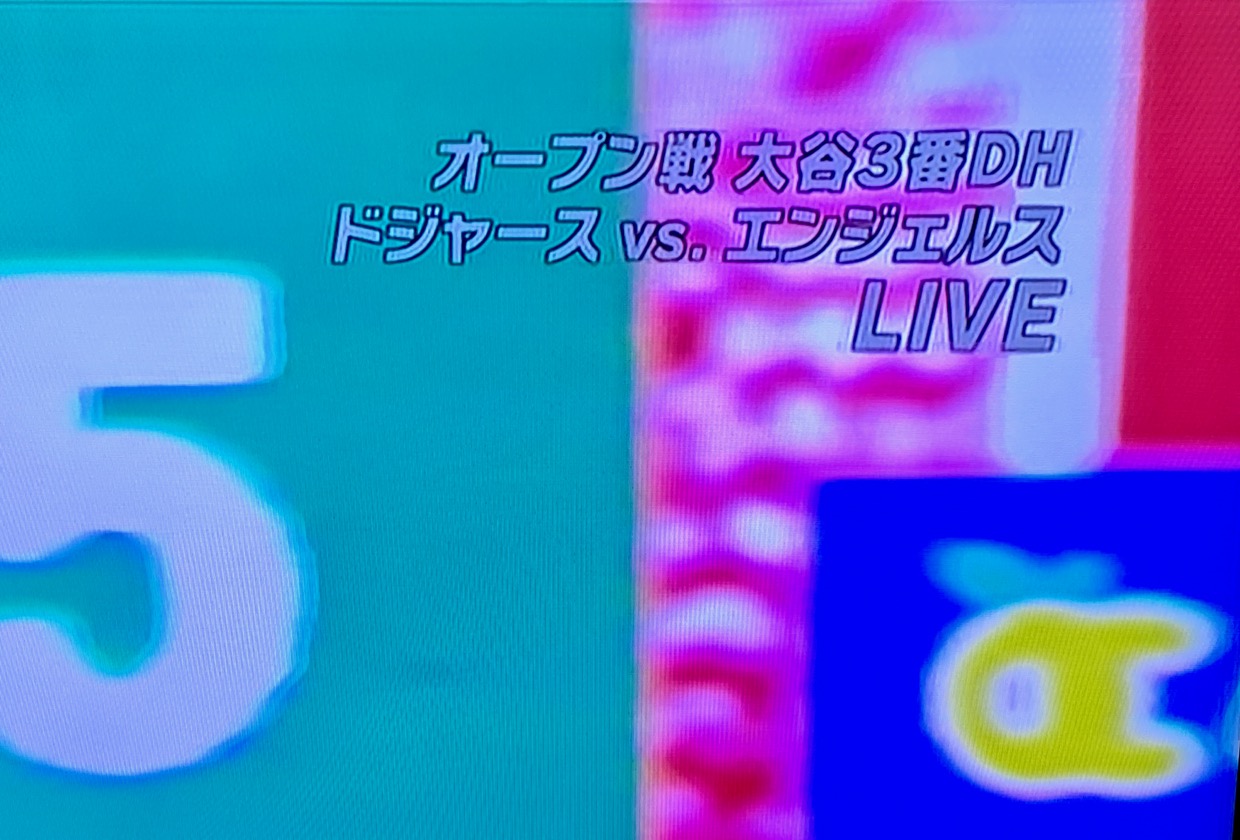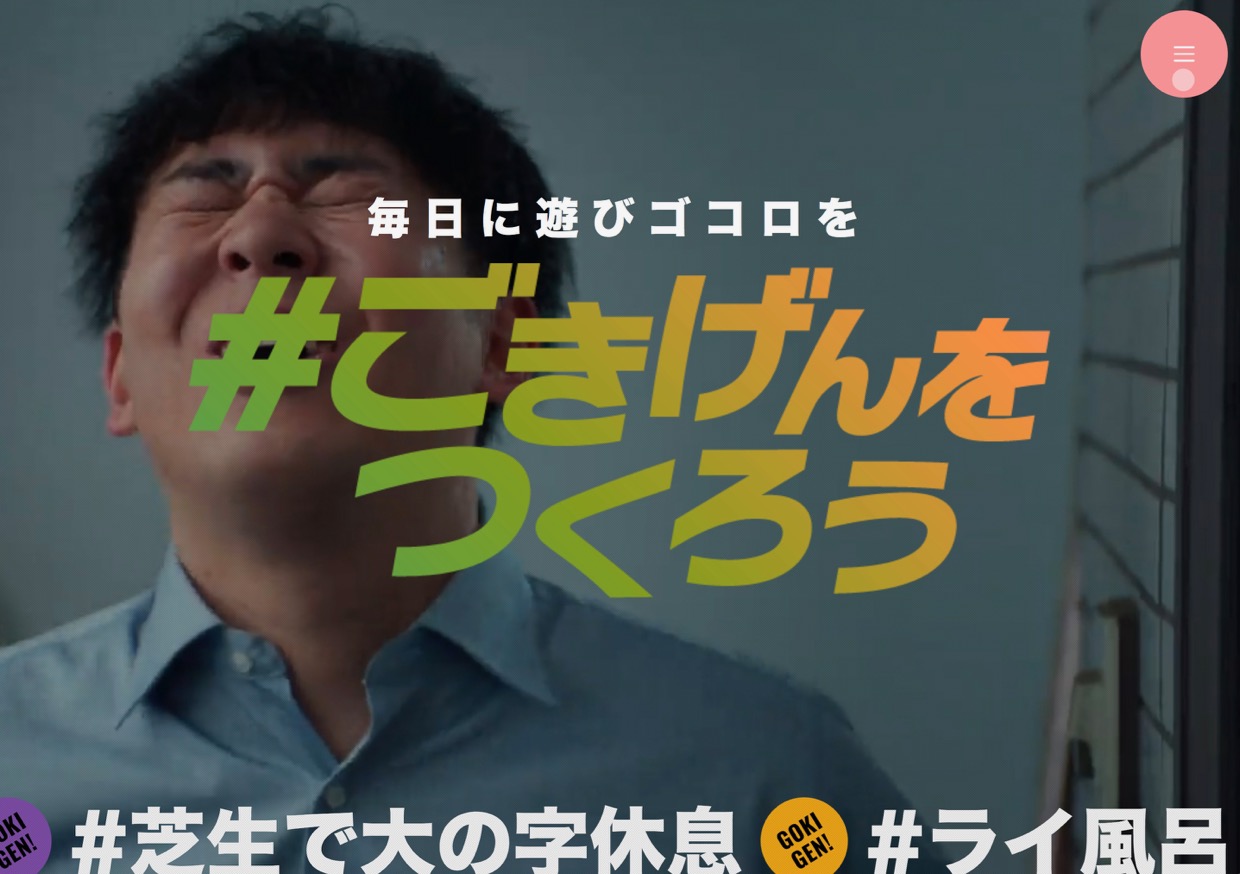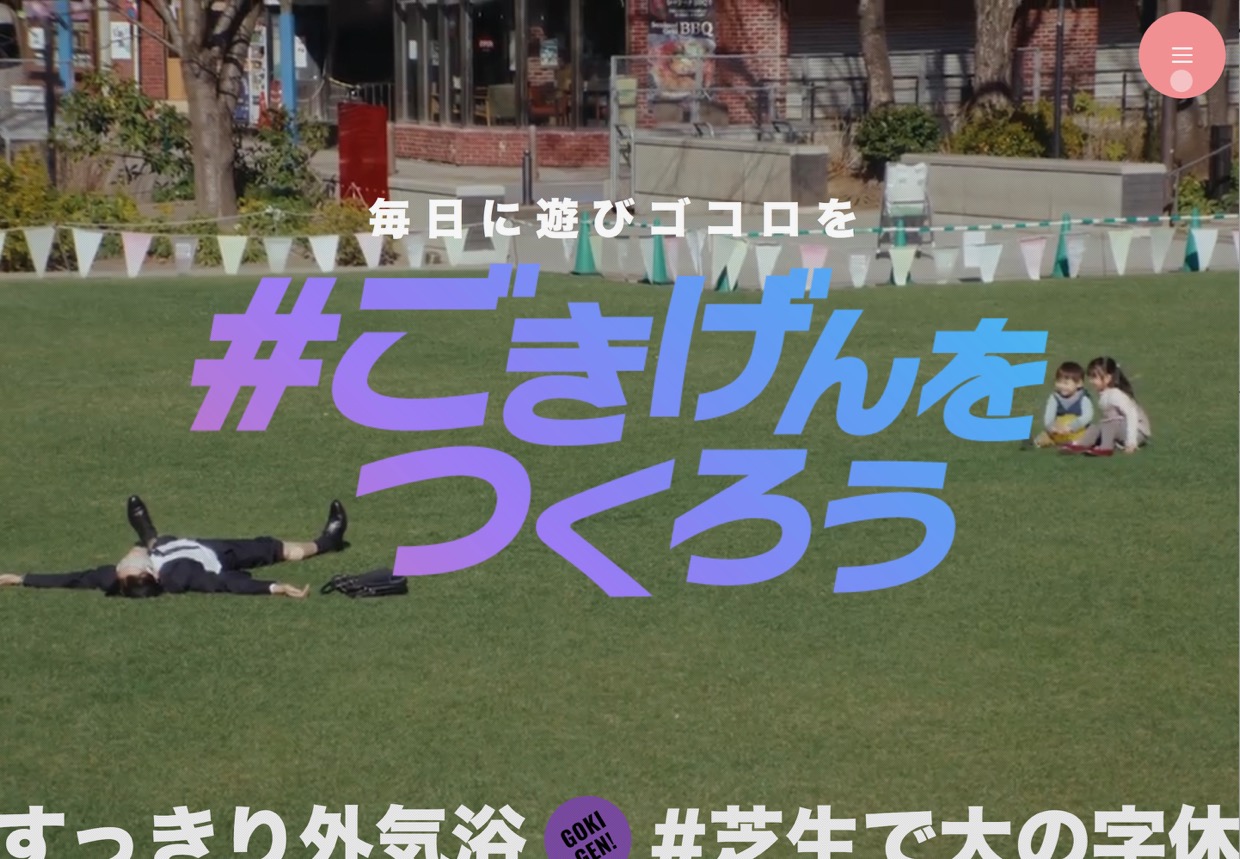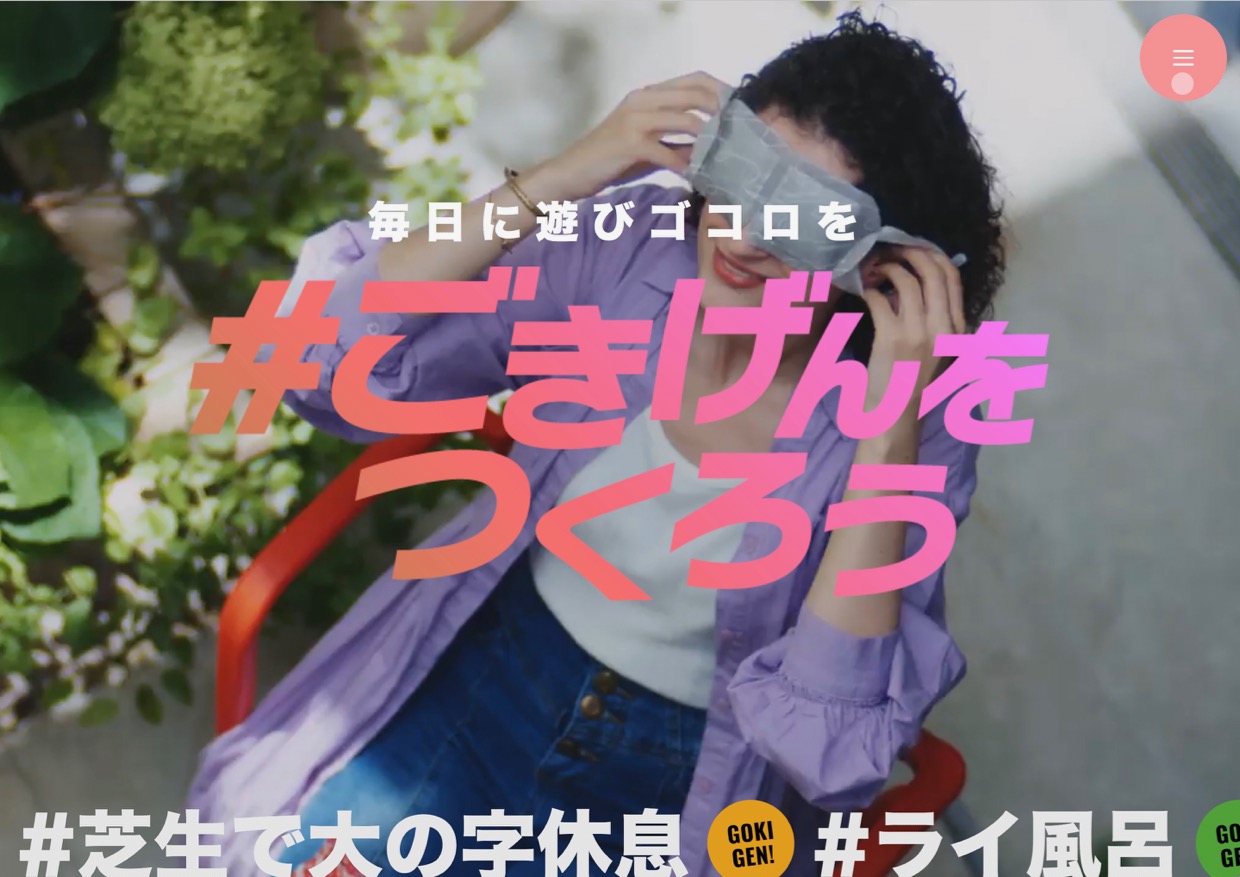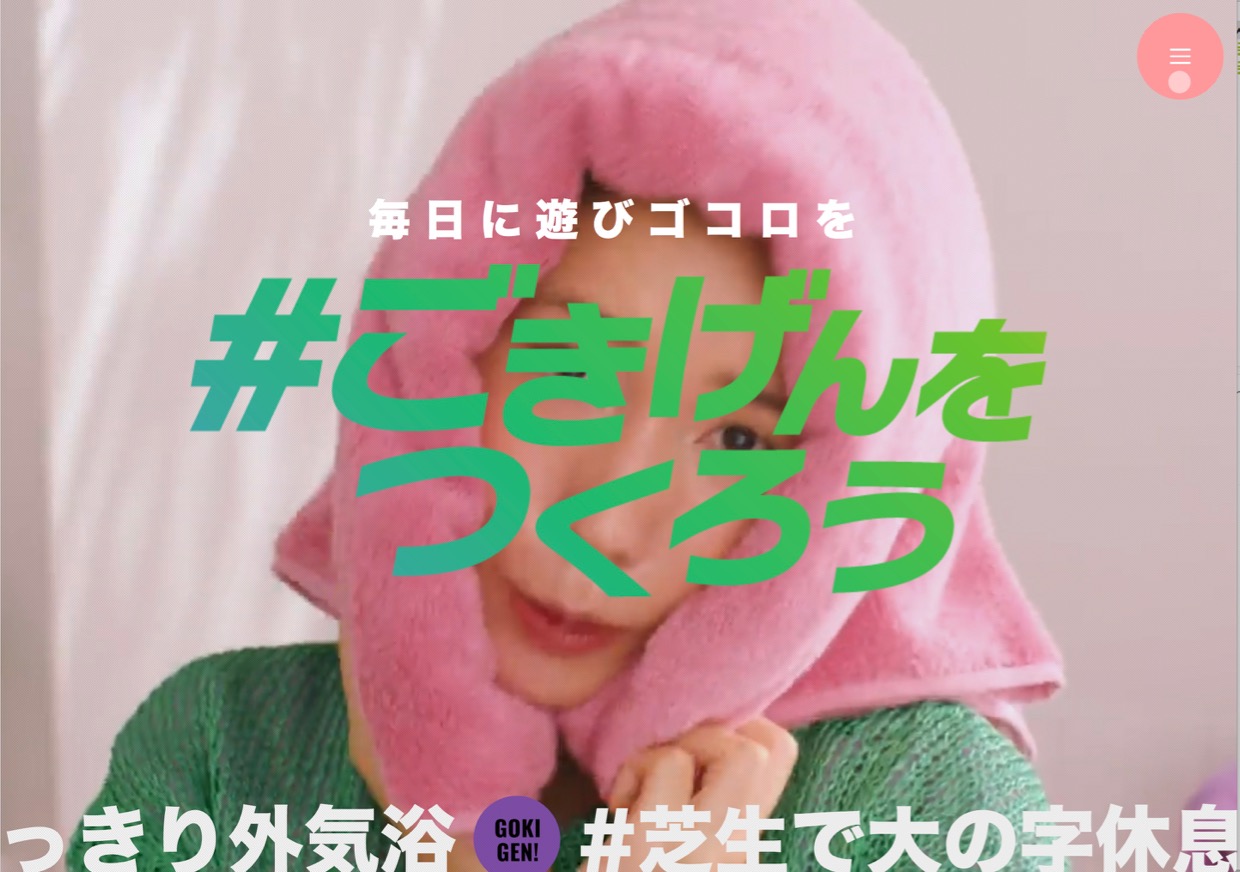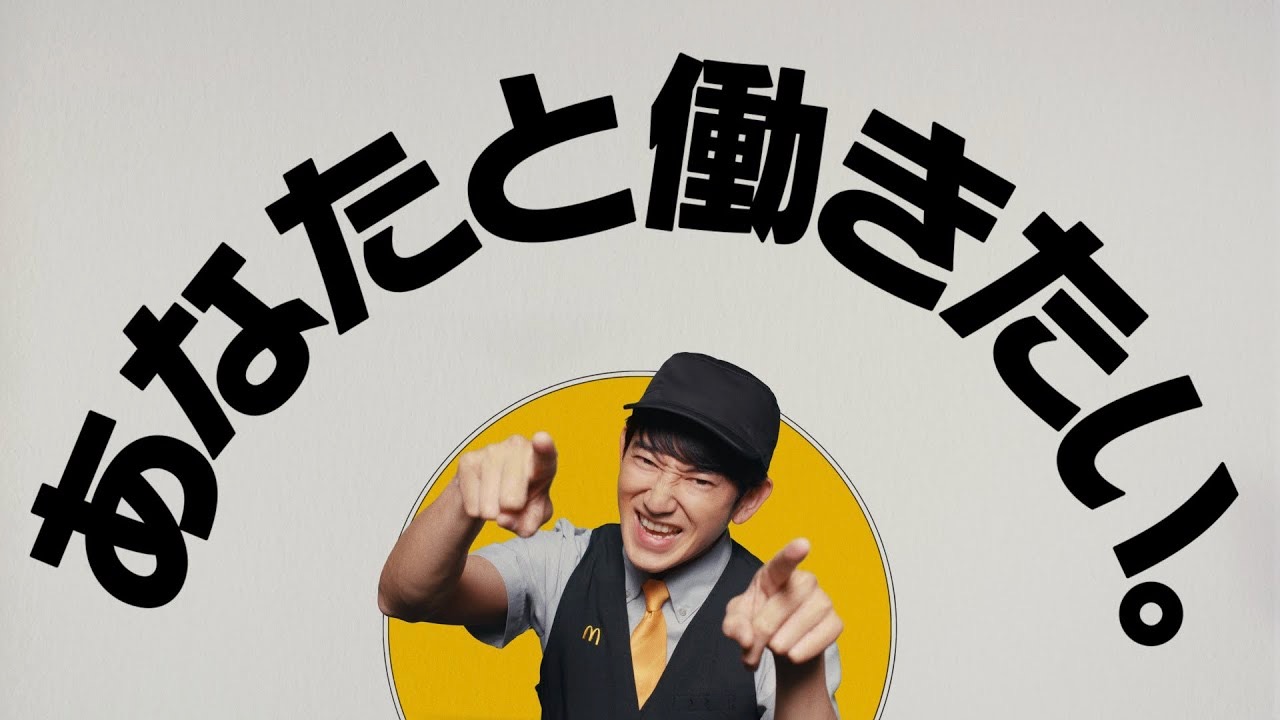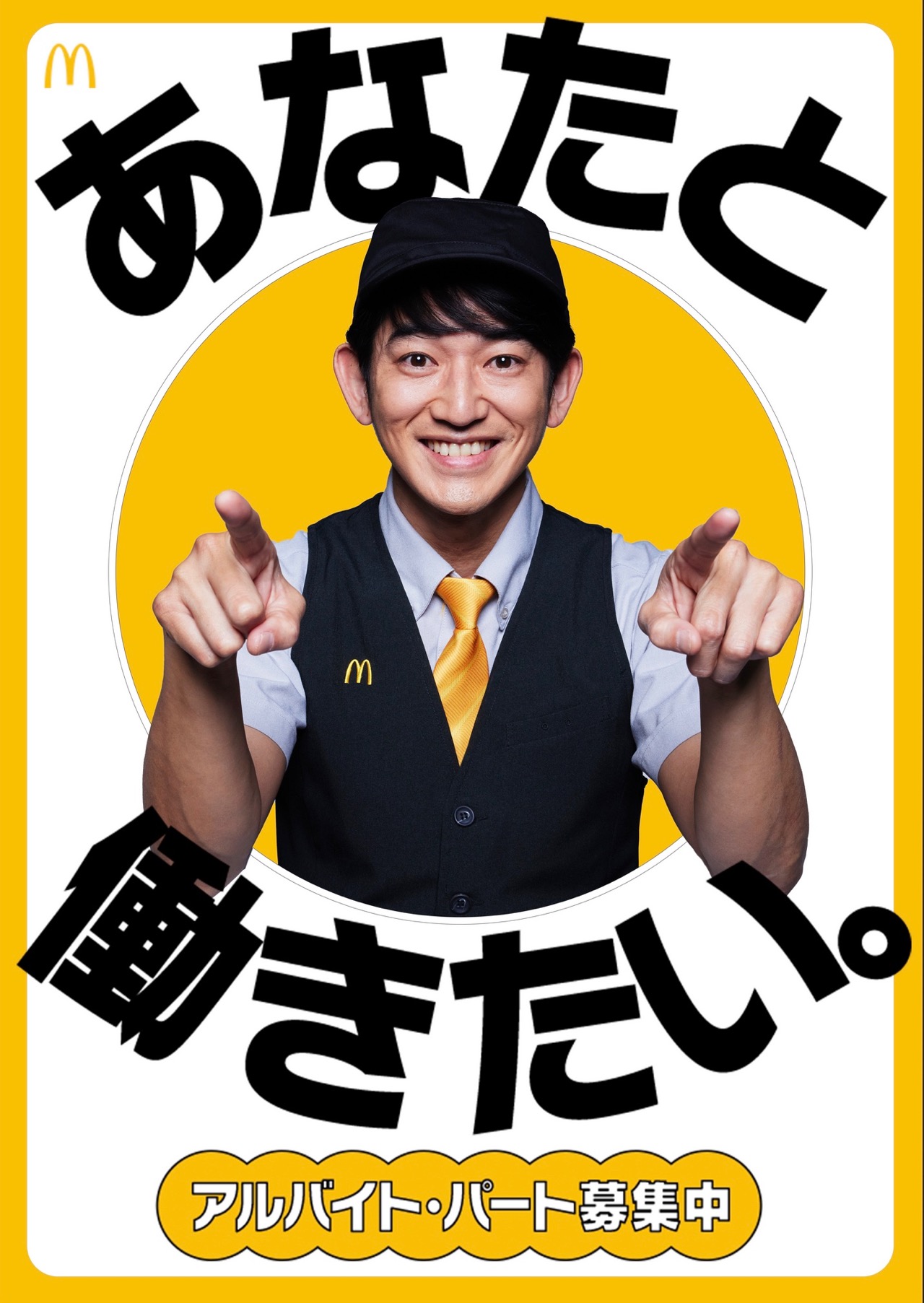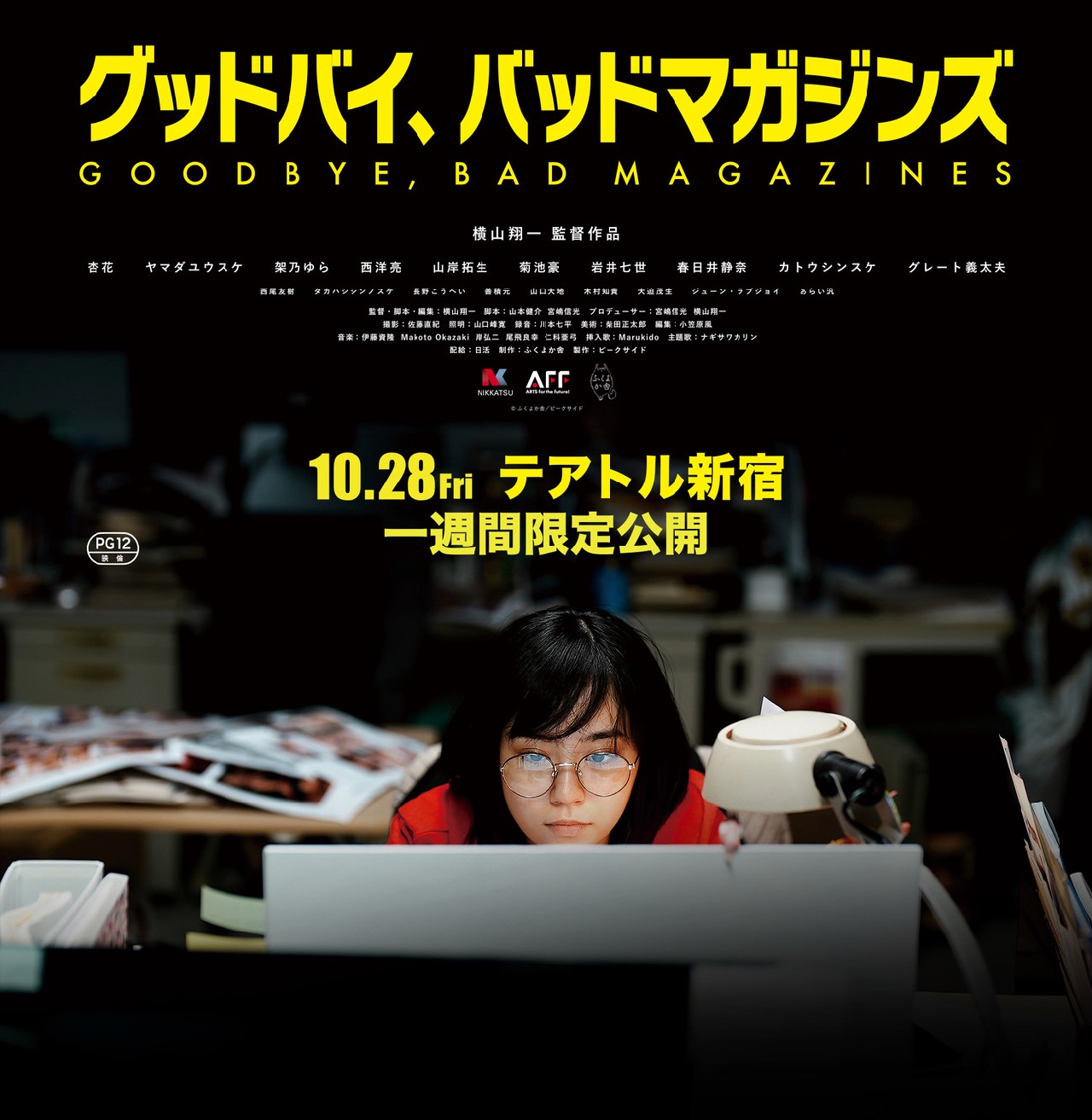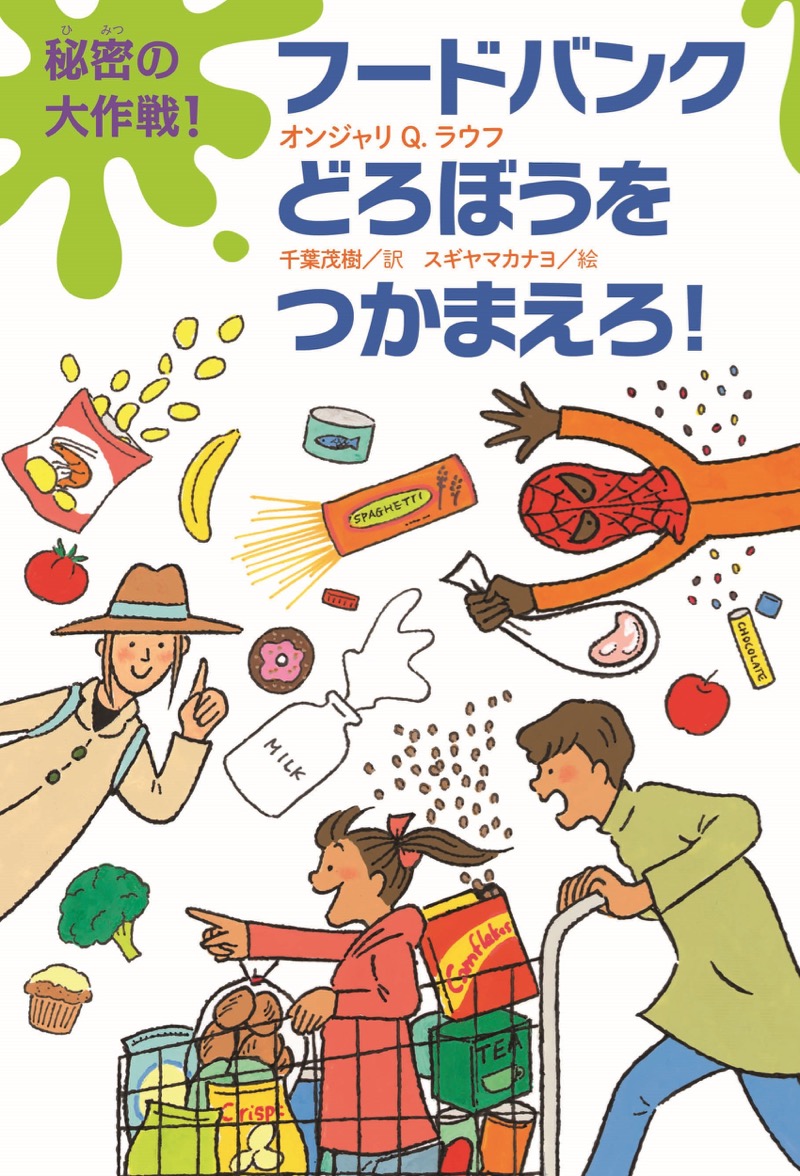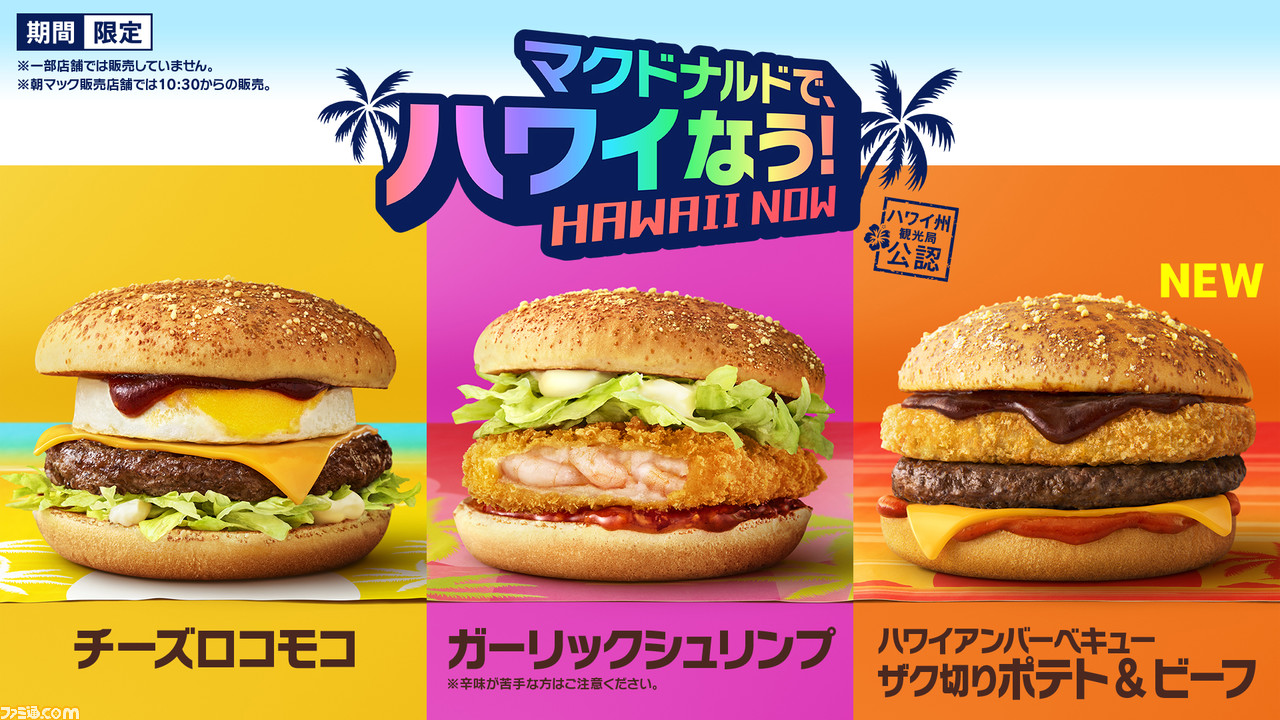
県民会館のロゴ さとうゆたか
ニタラゴルイカ。
すぐに捨てられるチラシとか、すぐに忘れられる広告での使用より、こういう建築物に使われると私の書体が永く残ってウレシイ(撮影者に感謝)。
トーサイクラシックホール岩手(岩手県民会館)。
広告画像 さとうゆたか
昨日から大量に露出している楽天の広告。
「チ」の1画目が、オリジナルとは違う形に加工されている…。
フェイスタオル さとうゆたか
ソフトバンクホークスの応援タオル。
あ さとうゆたか
実際の使用例(撮影者に感謝)。
新聞記事タイトルロゴ さとうゆたか
読売新聞 毎月第2、第4土曜日に連載される「おでかけエクササイズ」。
これは、動画のタイトル。
カンテレの番組 takumi
関西テレビの番組「フットマップ」でのニタラゴ使用例です。
TRAIN TV 匿名
中央線の車内放送で、使用されていました
下部の文字がニタラゴルイカで、上部の文字はルイカのようです。
もうひとつ。
映画タイトル さとうゆたか
クルックス | Netflix公式サイト
もうひとつ。
マインクラフト さとうゆたか
書名:はじめてのマインクラフト サバイバル図かん
著者:Minecraft
発行:KADOKAWA
書名:マインクラフト まちがいさがしサバイバル
著者:Minecraft
発行:KADOKAWA
プラモnoハナシ さとうゆたか
毎週日曜午前10時~ テレビ東京『プラモnoハナシ』
もうひとつ。
テレビ番組 さとうゆたか
テレビ東京の、タクシー運転手さん 一番うまい店に連れてって!
まだある。
もうひとつ。